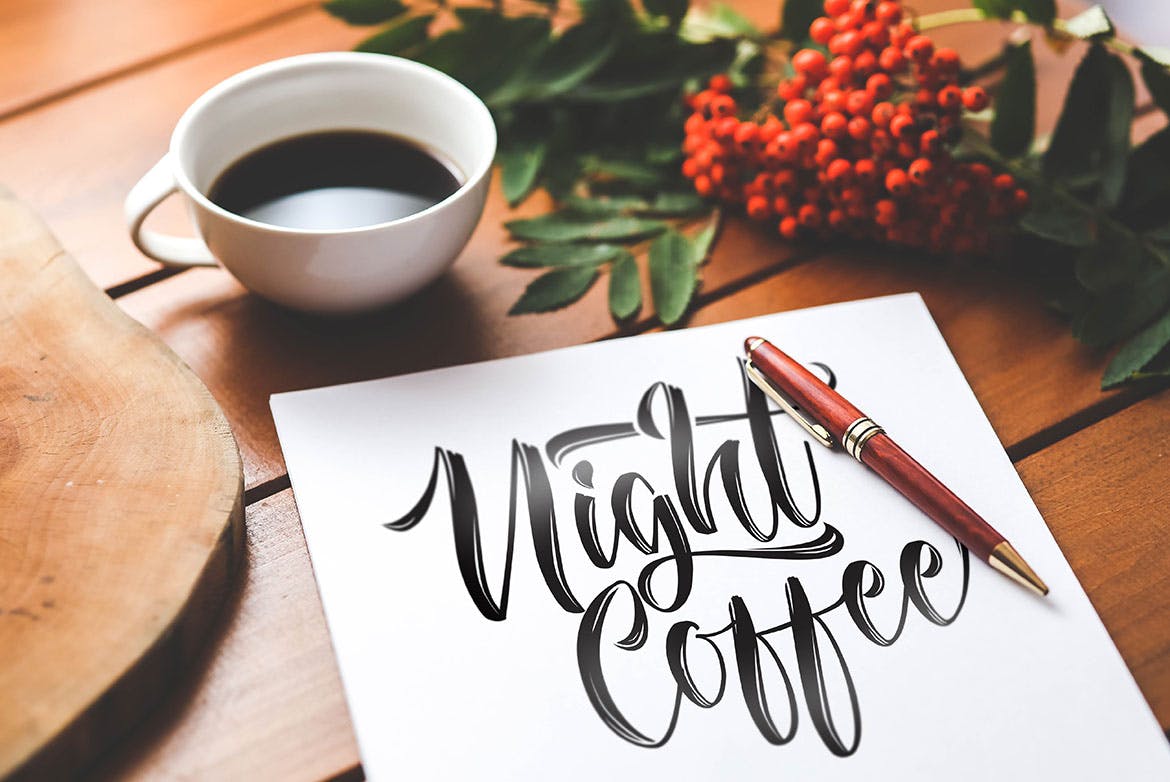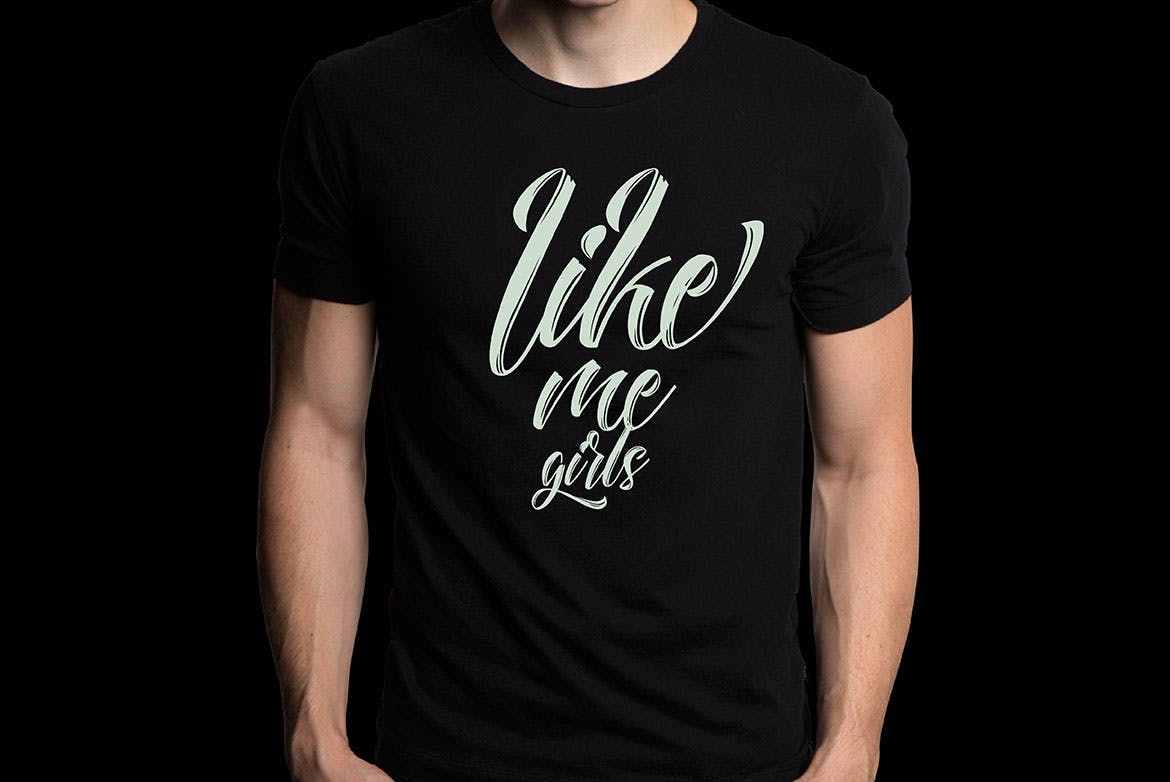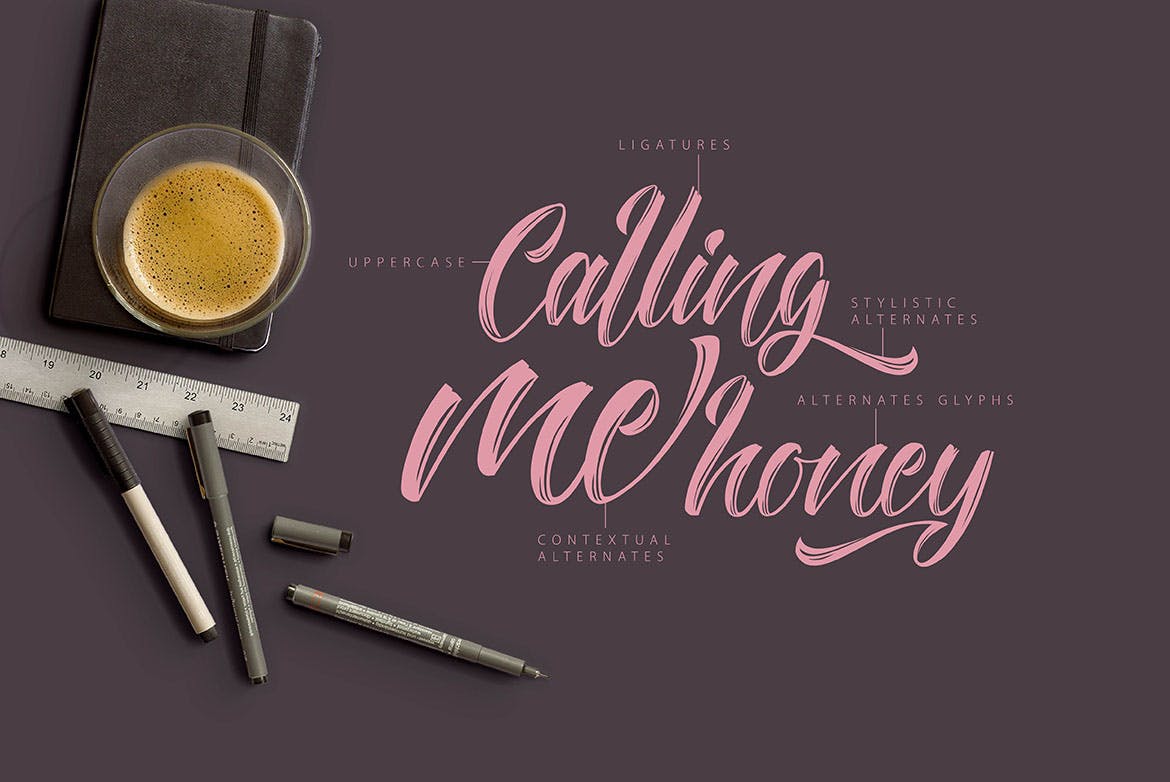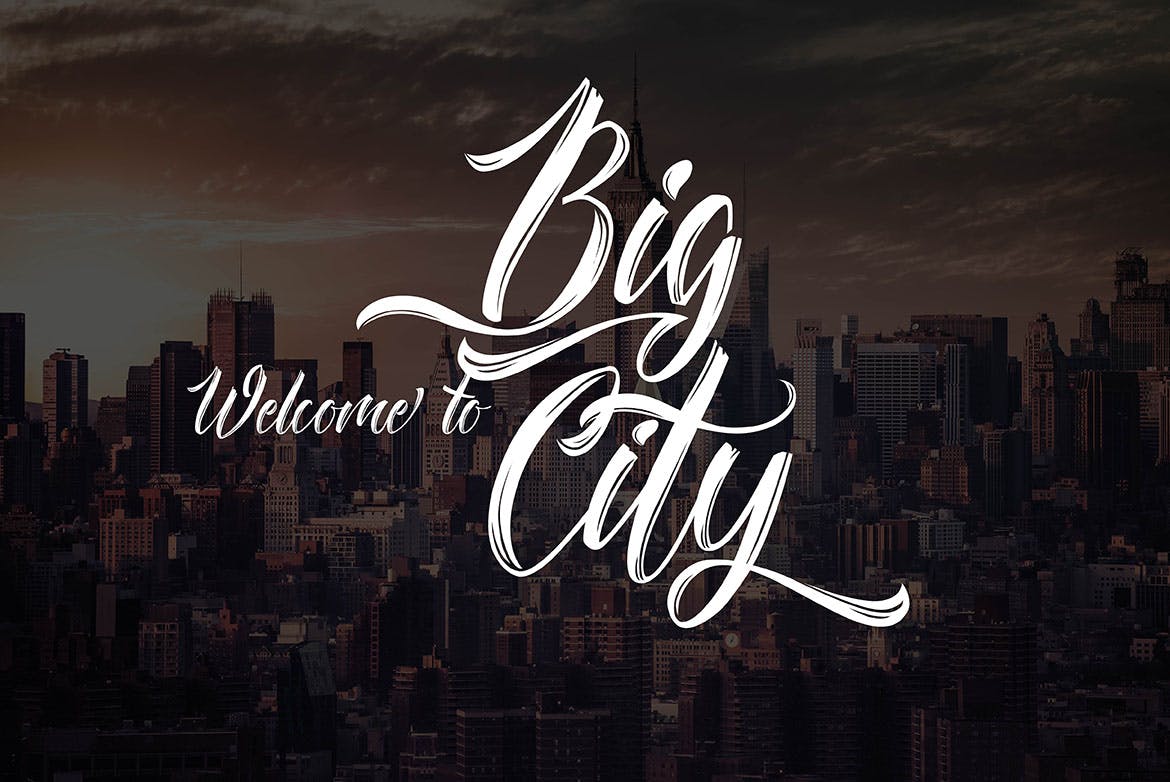
Amylight là một kiểu chữ thư pháp đẹp, lý tưởng cho thiệp mời đám cưới, thiệp chúc mừng, áo phông, logo hoặc bất kỳ thiết kế nào bạn tạo ra. Amylight đi kèm với các ký tự tiêu chuẩn, dấu câu, ký tự quốc tế. Các ký tự thay thế được chia thành nhiều tính năng OpenType như Ligature, Alternates và đưa ra Unicode PUA (Phông chữ được mã hóa đặc biệt)
Đặc trưng
- CHỮ IN HOA
- nhỏ xíu
- chữ số
- chấm câu
- ký tự quốc tế
- Chữ ghép
- Lựa chọn thay thế mang tính phong cách
- Hỗ trợ Unicode PUA